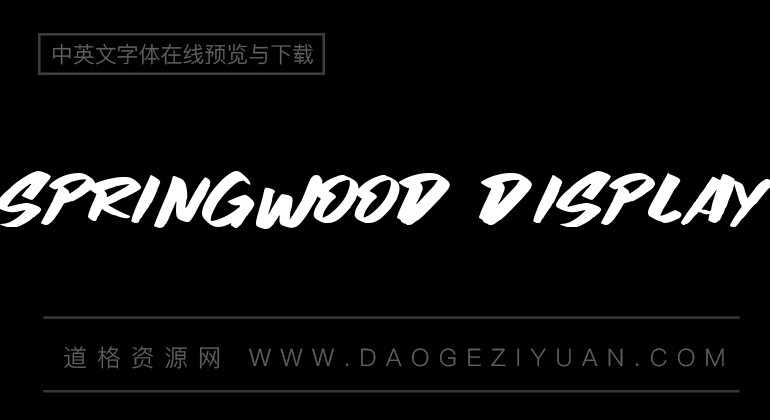
Springwood Display是一款非常优雅的英文字体,它拥有自然、柔和的风格,适合用于报纸、杂志、海报等印刷品的设计中。它具有较强的表现力,可以给文字增添色彩,提升文字的表现力。它的字体线条清晰,字形稳定,可以更好地表达文字的意思,让文字更加动人。内容介绍
Springwood Display是一款非常不错的手写艺术字体,具有很好的视觉感,适合于文化类的宣传设计、商业类品牌的广告和产品包装设计以及个性化文字排版等较多场景。